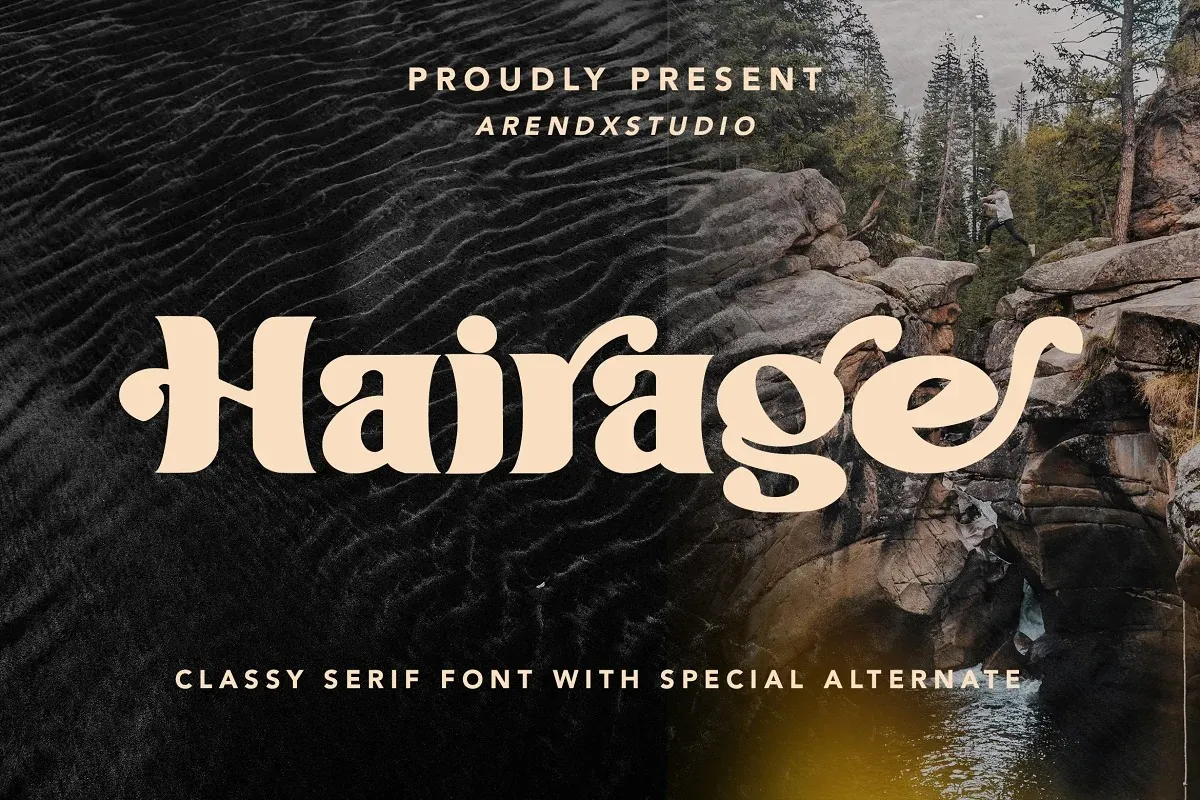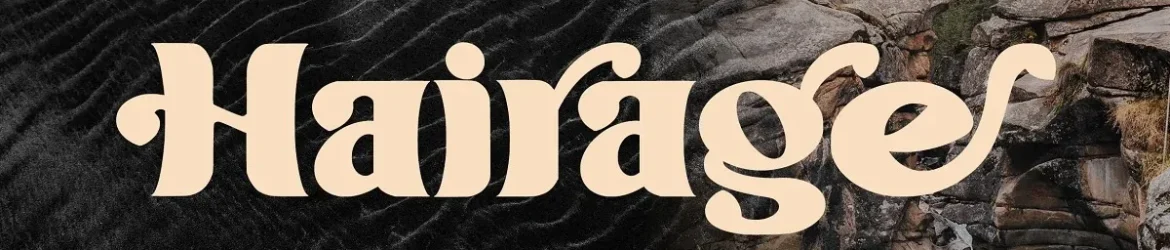
A Hairage Font é uma tipografia séria vintage com aparência agressiva criada por Arendxstudio, caracterizada por sua personalidade forte e traços suaves. Esta fonte perfeita para projetos de marca, logotipos, desenhos de casamento, posts da mídia social, anúncios, embalagens de produtos, design de produtos, rótulos, fotografia e até mesmo marcas na água, invitations e material de estação. Ela é perfeitamente adequada para qualquer projeto que exija um toque pessoal e autêntico. Composta por caracteres escritos a mão, ela traz uma personalidade única para o design, tornando-a ideal tanto para aplicativos digitais quanto para impressão em papel.